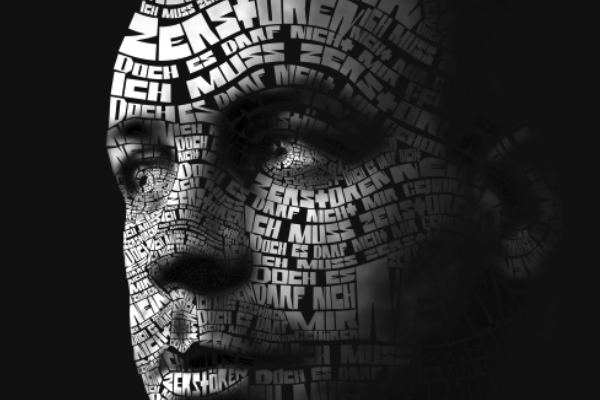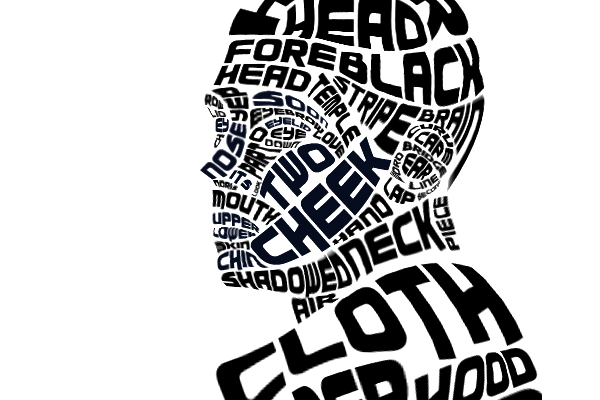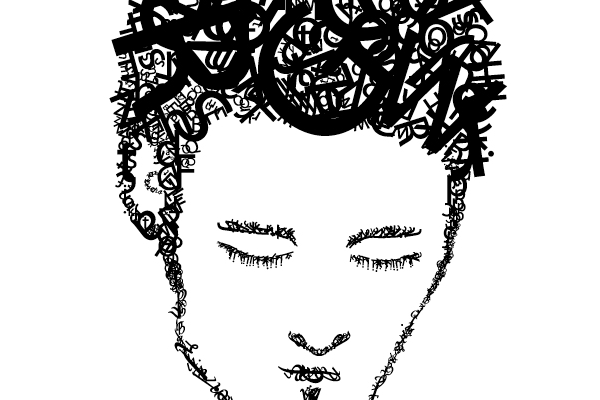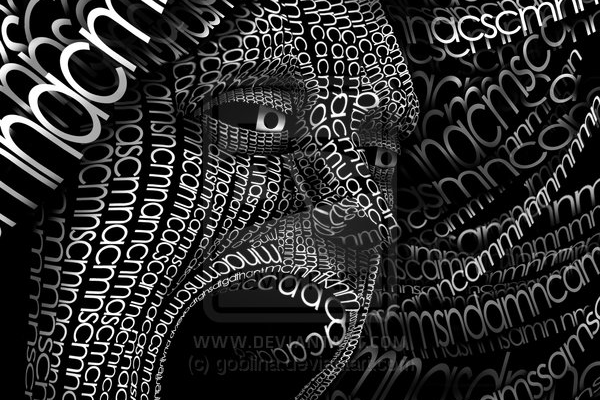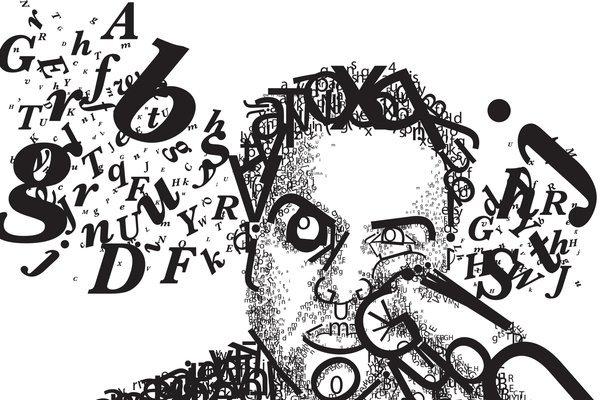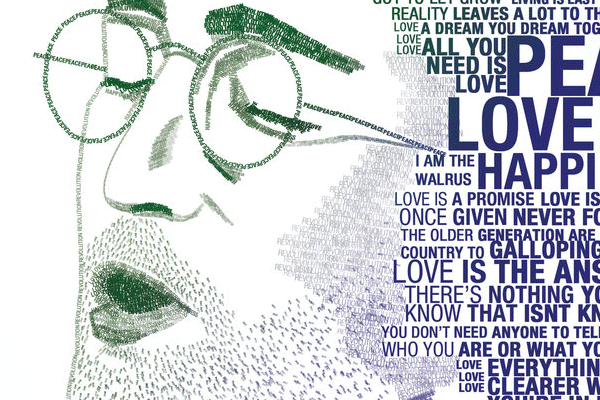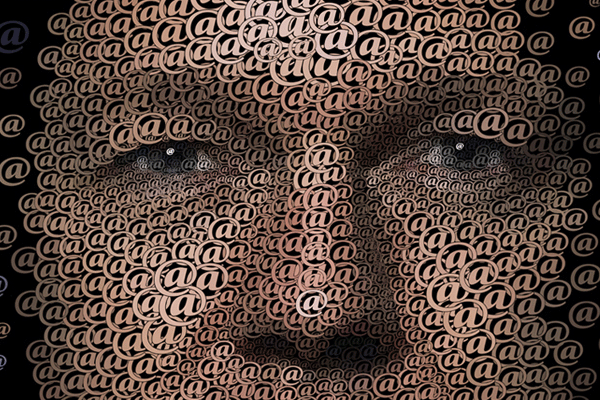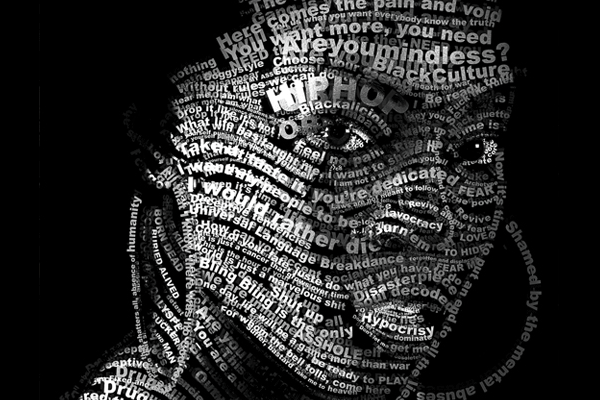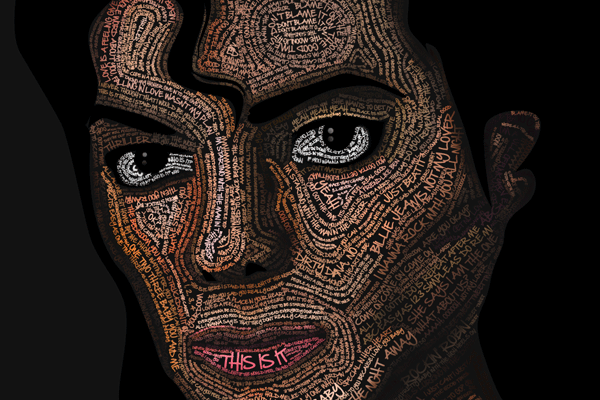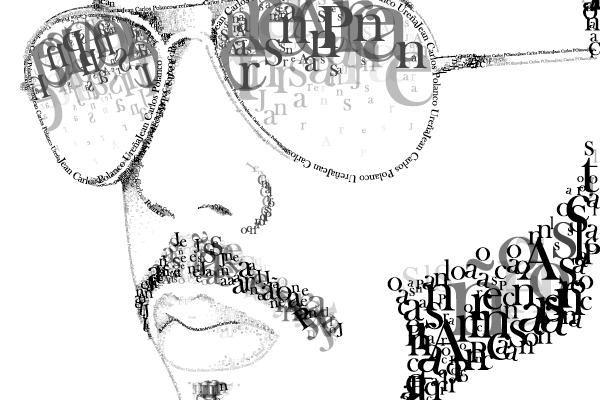
Tipografias de Rosto Criativas
Um estilo de arte muito legal é usar a tipografia para montar cenários, pessoas e objetos. Com variações de cores, fontes e tamanhos os artistas criam figuras criativas e inspiradoras. Listamos 30 exemplos desse método de criação para sua inspiração do dia, quem sabe você não use algo assim em suas artes de hoje. :D